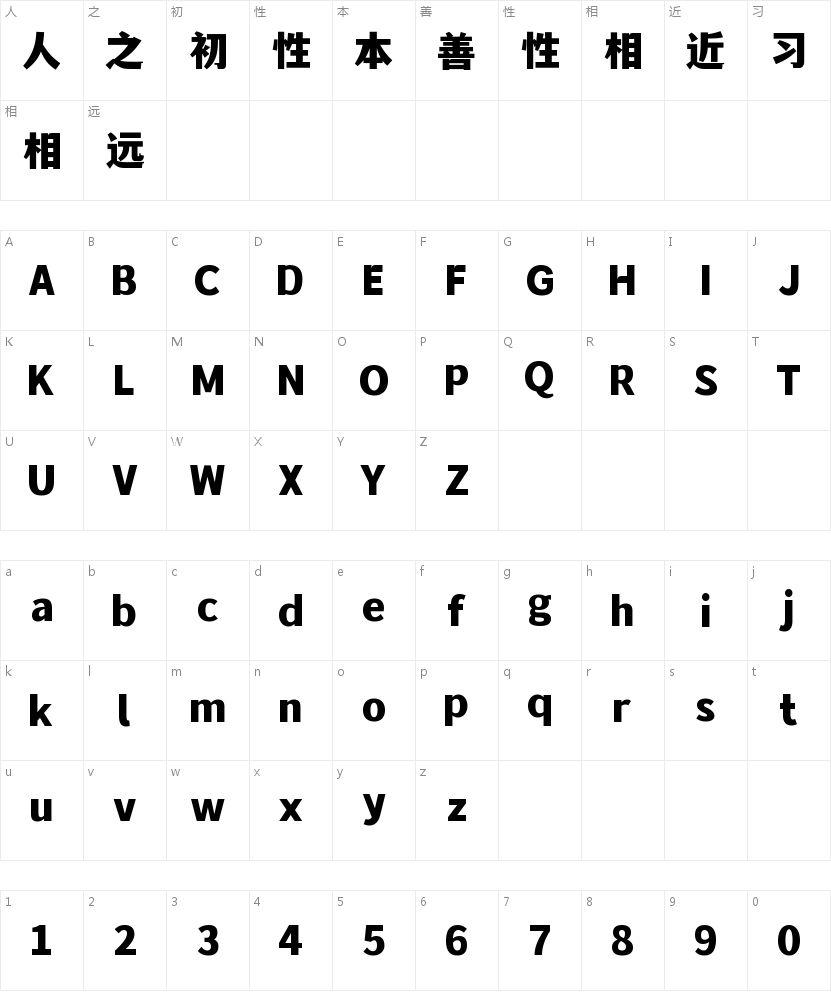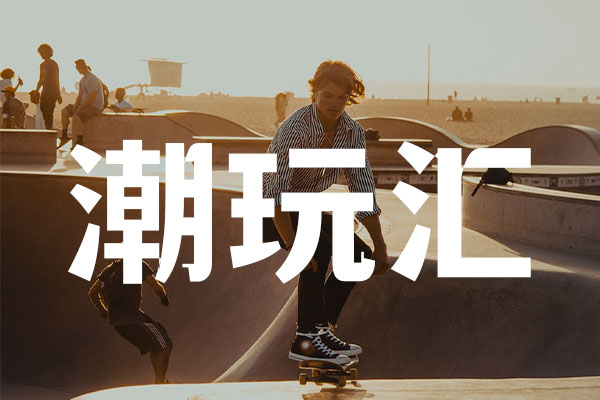
文道潮黑体,又名为WDCHT,是一种融合了典雅气质与潮流感的独特黑体字体。这款字体巧妙地结合了黑体的简洁线条和宋体的优雅特征,使得它在众多字体中独树一帜。
文道潮黑体的字形设计方正有力,给人一种刚柔相济的视觉感受。每个字形都经过精心设计,呈现出一种优雅大方的风格。无论是用于商业还是个人用途,都能表现出极佳的视觉效果。